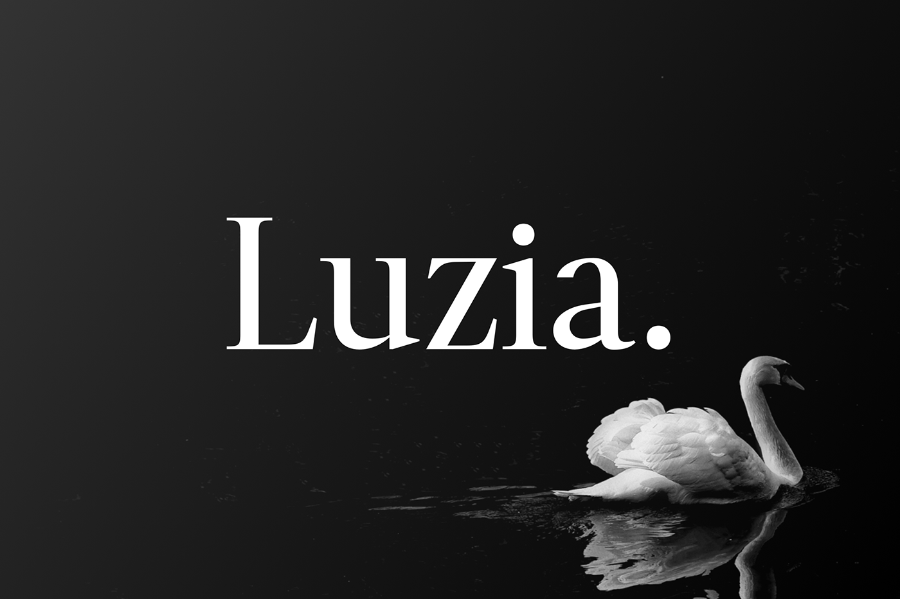
Descubra a exuberância e o encanto da Luzia Font Family, uma família tipográfica serifada criada por Hamilton para Quill Type Co. Esta fonte evoca um sentimento nostálgico e sofisticado, com um x-height marcante que proporciona uma letra fluida e vibrante. A familia de letras se destaca por sua riqueza em caracteres expressivos, oferecendo suporte a quase todos os idiomas europeus. Ela se adapta perfeitamente tanto para o texto principal quanto para títulos, tornando-a uma escolha ideal para qualquer projeto que exija um toque elegante e sofisticado. Uma verdadeira maravilha para designers gráficos em busca de estilo único e versátil.